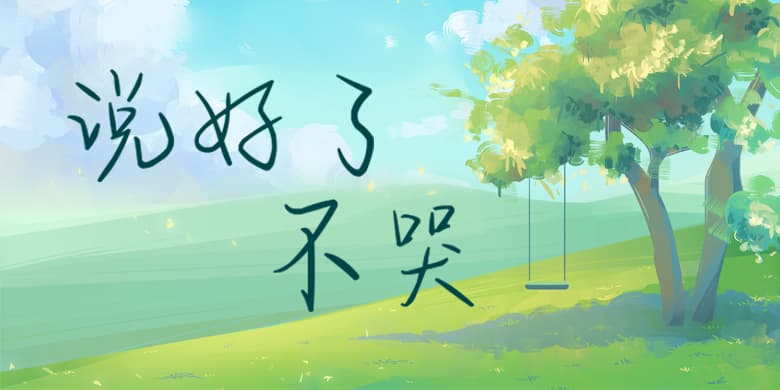
品牌:方正手迹设计师:俞亦婷发行时间:2019字库编码:大陆简体(GB2312-80)分类:常规书写·硬笔字体属性:精品字
行笔潇洒飘逸,结字富有变化,字体排版充满韵律,该字很好的传达出了洒脱不羁的风格特点。适用于现代诗歌、短文的排版以及文化、商业类品牌的广告语设计。
品牌:方正手迹设计师:俞亦婷发行时间:2019字库编码:大陆简体(GB2312-80)分类:常规书写·硬笔字体属性:精品字
行笔潇洒飘逸,结字富有变化,字体排版充满韵律,该字很好的传达出了洒脱不羁的风格特点。适用于现代诗歌、短文的排版以及文化、商业类品牌的广告语设计。